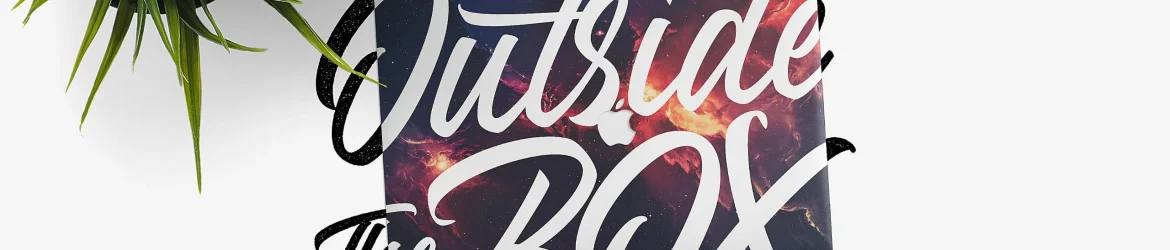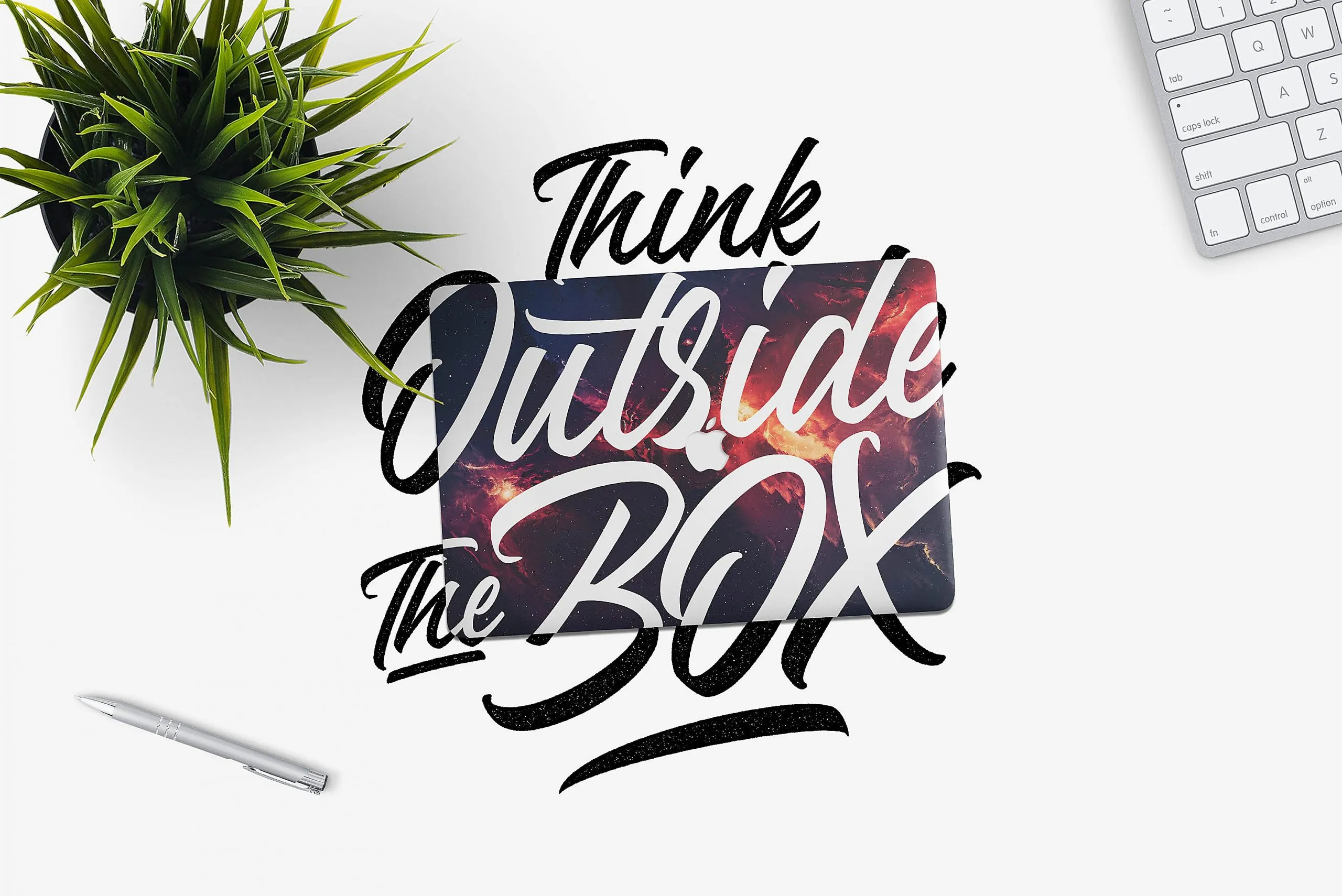
The Lunatique Script Font – Fonte Grátis
The Lunatique Script Font
Aproveite o novo dia com uma elegante fonta script brush. Introduzimos a fonte The Lunatique. A The Lunatique é uma fonte de script, com um estilo dinâmico e vibrante. Ela se destaca como uma opção versátil para várias finalidades. Use ela em títulos, assinaturas, logotipos, designs de camisetas, cartas de encargo, sinais, etiquetas, cartazes, selos, convites, entre outros usos. A The Lunatique é uma fonta que vai fazer a diferença em seus projetos. Comece cada novo dia com o frescor e estilo único desta fonte.